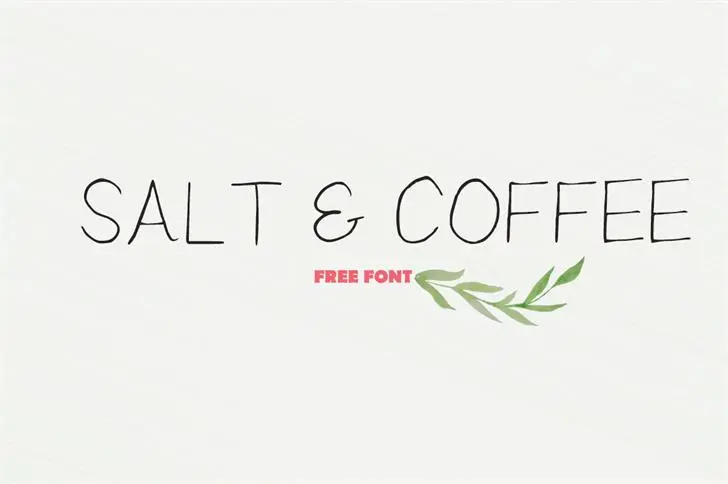
Salt Coffee Font – Fonte Grátis
Salt Coffee Font
A fonte “Salt Coffee Font” é uma elegante cauda escrita a mão que transmite energia e diversão. Ideal para aqueles projetos onde você deseja dar um toque único com sua personalidade, essa fonte pode ser combinada de forma única com outras fontes script ou tipo regular. Ela não apenas adicionará um ar criativo às suas criações, mas também uma sensação agradável e vibrante à sua identidade visual. Criativacos é o designer responsável por esse encantador projeto de tipos, que traz para você um upgrade visual divertido para seus materiais digitais. Aproveite a oportunidade de dar vida à sua marca com essa fonte singular e envolvente.